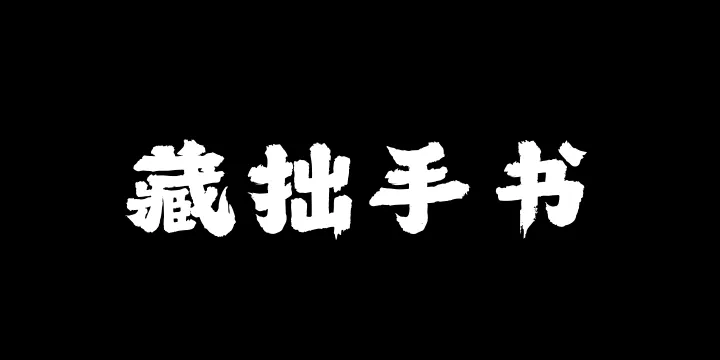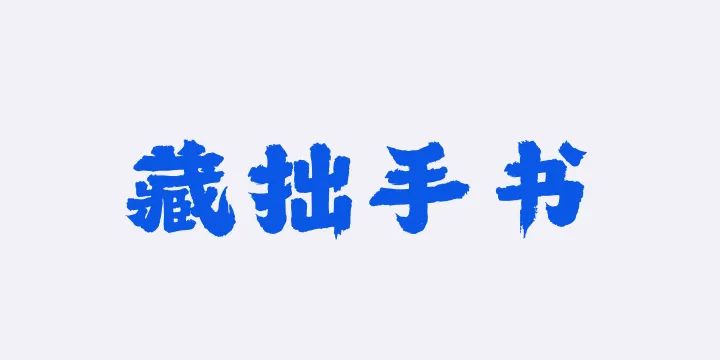
山海藏拙手书W By 山海字库 商用字体
字体全名: 山海藏拙手书W
字体简介: 山海藏拙手书,是一款全新的毛笔风字体,包含汉字9169个,符号200+个。该字体的毛笔笔锋狂野有力,同时又朴拙浑厚,非常醒目!字形古朴浑厚,在浑厚的同时而又极富张力。它的笔画充满力量感的同时,用蕴含着朴拙感。在粗细的纵横间,拥有非常规的张力特性。笔画的飞白效果使字体的气息更加流畅,笔画间的关系密不可分,同时也增加了字体的自由洒脱之感。
所属分类: 手写体书法